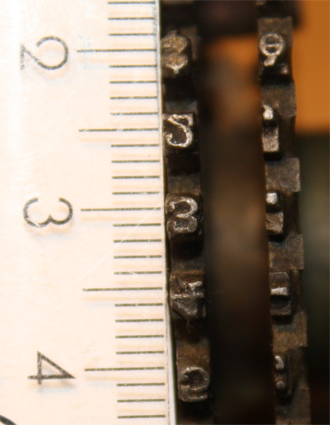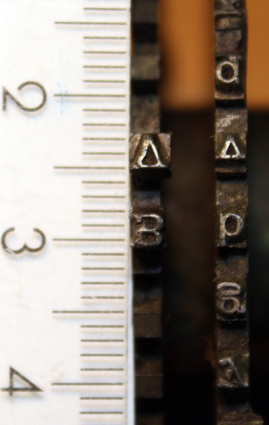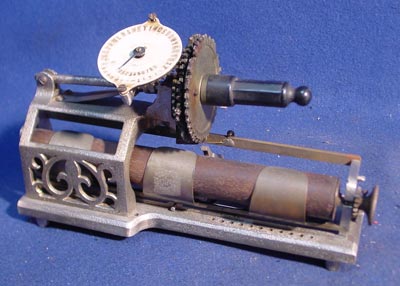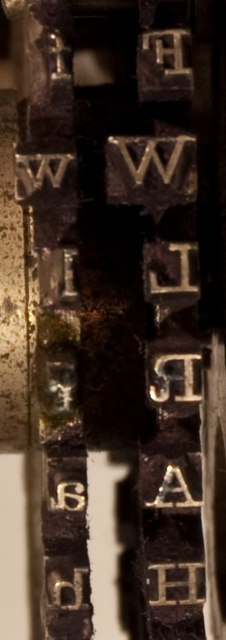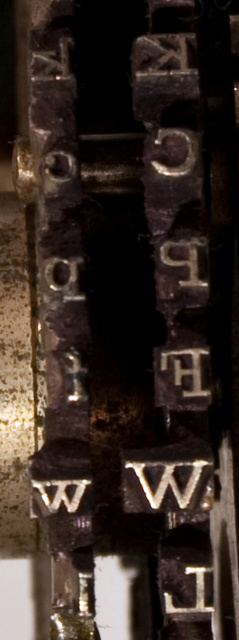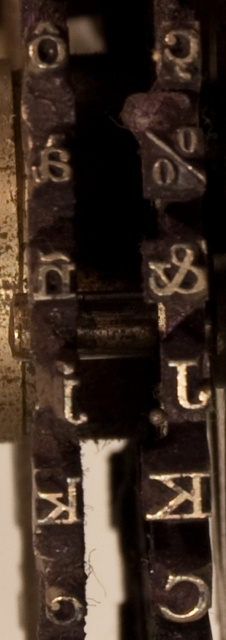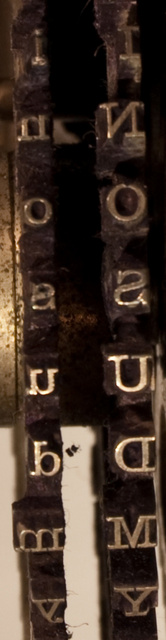
Schreibmaschine 1885
Da ich ein "Newbie" in diesem Forum bin, hoffe ich die richtige Kategorie für meine Frage erwischt zu haben. Auf einer Schreibmaschine mit Proportionalschrift aus dem Jahre 1885 fehlen eine Reihe von Typen. Auf der Maschine sind nicht die "typischen" Steck- oder Schuhtypen wie sonst üblich angebracht, sondern, so vermute ich, Typen aus dem Druckgewerbe. Da eine Reihe von Typen fehlen, richte ich mich an die Forumsmitglieder um Hilfe.
Um welche Schriftart handelt es sich und um welche Art von Typen?
Ein weites Feld … kannst Du bitte sagen wie der Hersteller heißt und wie die Typenbezeichnung lautet? Schreibmaschinen mit proportionale Schrift sind glaube ich eher selten gewesen. Einer der Hersteller der auf jeden Fall bis in den 1960ern mit solche Maschinen international erfolgreich war ist AM Varityper. Die Produkte sind bekannt als Adressograph, Multigraph und Varityper. Habe hiervon ein Schriftmusterbuch. Reinschauen macht aber nur Sinn wenn ich weiß, ob es sich wirklich um so eine Maschine handelt. Die Schriftart deiner Maschine hat es bei sehr vielen Herstellern in ähnlichen Ausführungen gegeben und die meisten Hersteller haben (wenn sie überhaupt welche hatten) eigene Bezeichnungen für die Schrifttypen gehabt.
Varityper mit proportionalschrift
anderes Modell:
Hammond Varityper
Hier sieht man die Typenplatten der Varityper. Das Schriftmusterbuch was ich habe enthält Schriften die auf diese Typenplatten verfügbar waren. Bei deine Maschine scheint es aber um ein anderes Schriftträgersystem zu handeln.
Bei der Maschine handelt es sich um die von Charles Spiro erfundene „Columbia Type-Writer“ in der ersten am Markt erschienenen Ausführung
Die Typen sind außen auf einer Typenscheibe angebracht, wobei eine Scheibe Groß- die andere Kleinbuchstaben und Sonderzeichen trägt (Modell 2 hat diese auf einer Scheibe vereinigt). Bis dato habe ich keine Unterlagen zu den damals angebotenen Schriftarten gefunden. Die zwei weiteren mir noch bekannten Maschinen haben ebenfalls die gleiche Schriftart. Zu dieser Zeit gab es bereits Typen speziell für Schreibmaschinen, die aber bei dieser Maschine nicht zur Anwendung kamen. Meine Vermutung ist, dass Typen aus einem Drucksatz verwendet wurden. Da ich die fehlenden Typen eventuell ergänzen möchte, bin ich auf der Suche nach der Schriftart und den verwendeten Typen.
Die von Dir erwähnte Varityper war übrigens 1885 auch schon sehr erfolgreich am Markt, da sie ein schönes, gleichmäßiges Schriftbild lieferte. Unter dem Namen „Hammond“ war sie bis zum Namenswechsel in den späten 20er Jahren sehr erfolgreich. Die Proportionalschrittschaltung kam aber erst später hinzu, wobei im späten 19. Jahrhundert noch einige Maschinen mit Proportionalschritt angeboten wurden.
Vielleicht hat jemand doch eine Idee um welche Schrift und Typen es sich handelt.
Um die Schrift einwandfrei identifizieren zu können, bzw. festzustellen welche Schrift(en) diese am ähnlichsten sind, ist es erforderlich, dass du mit mehreren Abbildungen möglichst alle Schriftzeichen zeigst. Momentan fehlen Schlüsselbuchstaben wie e, a und s.
Ich denke schon, dass es sich hierbei um eine speziell für diese Schreibmaschine angepasste Schrift handelt. Es sieht danach aus, dass der Strichstärkenkontrast relativ niedrig ist und dass die Ober- und Unterlängen relativ kurz sind. Prinzipiell sind alle Schreibmaschinenschriften nach dem Vorbild vorhandener Schriften gezeichnet bzw. gestaltet worden. Es fragt sich nur wie groß die Abweichungen sind.
Ein Kollege aus Kanada hat mir Bilder mit den Typen seiner Columbia zur Verfügung gestellt. Das erste Bild zeigt die Anbringung der Typen auf der Scheibe.
Die Schrift deiner Columbia sieht aus wie eine Clarendon. Also serifenbetonte Antiqua mit klassizistischem Charakter. Ähnlich könnte auch die spätere IBM Bold Face sein. Ursprünglich für die ebenfalls proportionale IBM Executive Schreibmaschine, später gab es die Schrift auch für den IBM Composer und für die IBM 50, ebenfalls Schreibmaschinen mit proportionale Schriften.